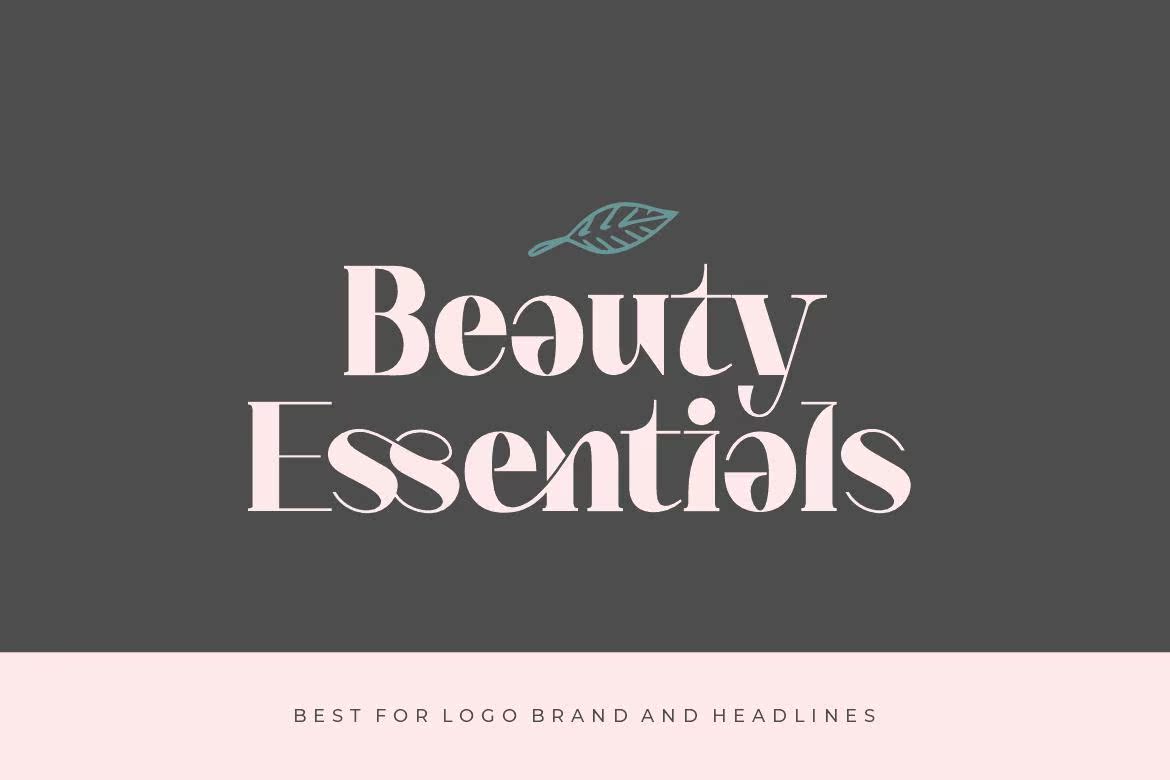
Not TED是一种独特且有趣的系列字体,具有那种复杂的感觉。这种字体完美地融入了经典的模板和徽标中。它具有唯一的功能和大写字母以及编号,标点符号和多语言字母。NotTed是一个独特且有趣的系列字体,具有复杂的感觉。该字体完美地融入到经典模板和徽标中。它具有单大写字母和大写字母以及字母、标点符号和多语言字母。